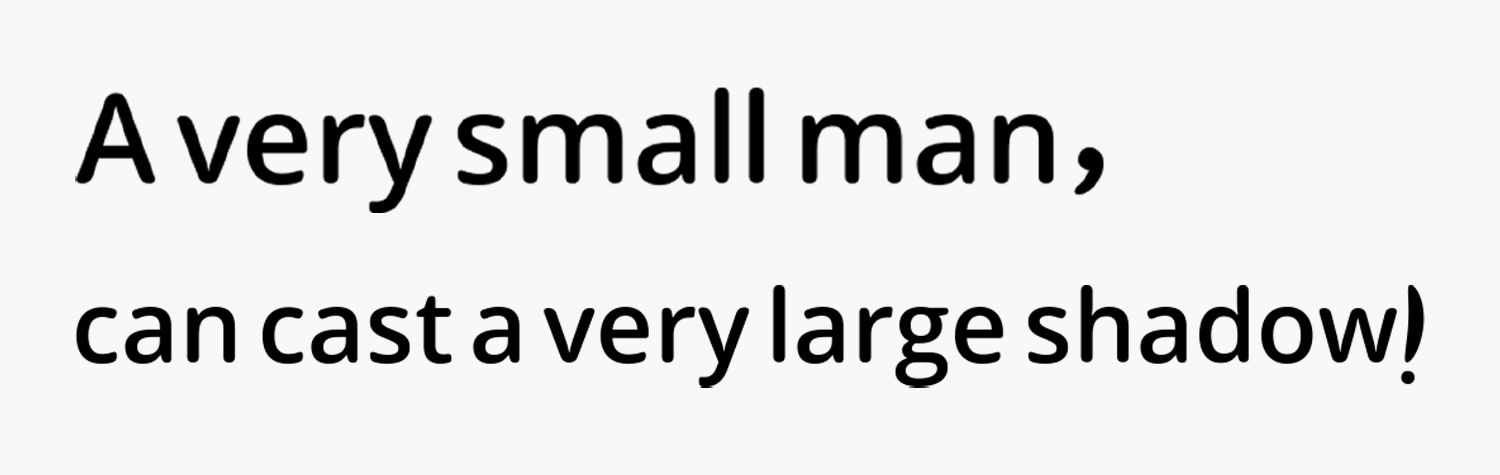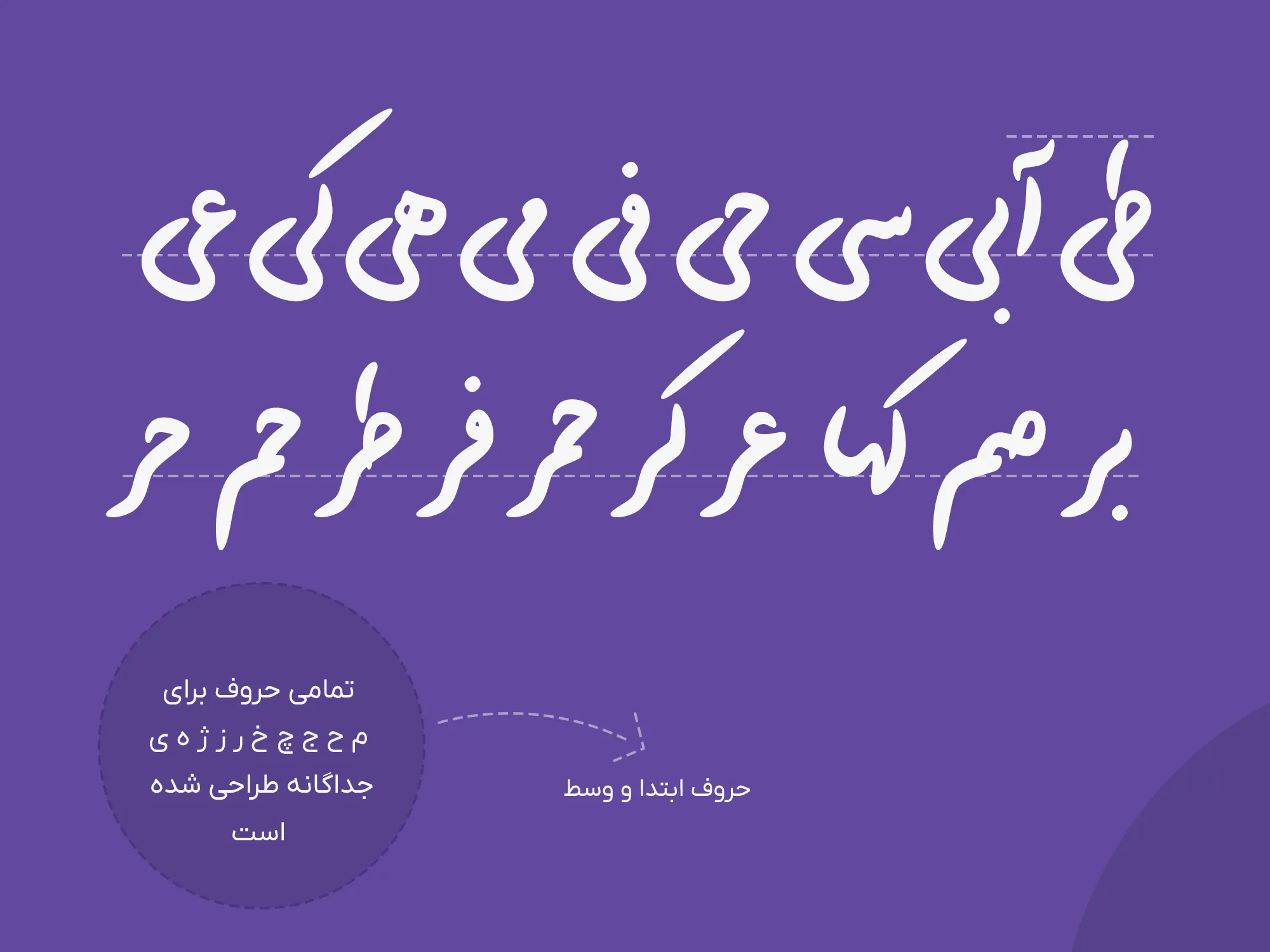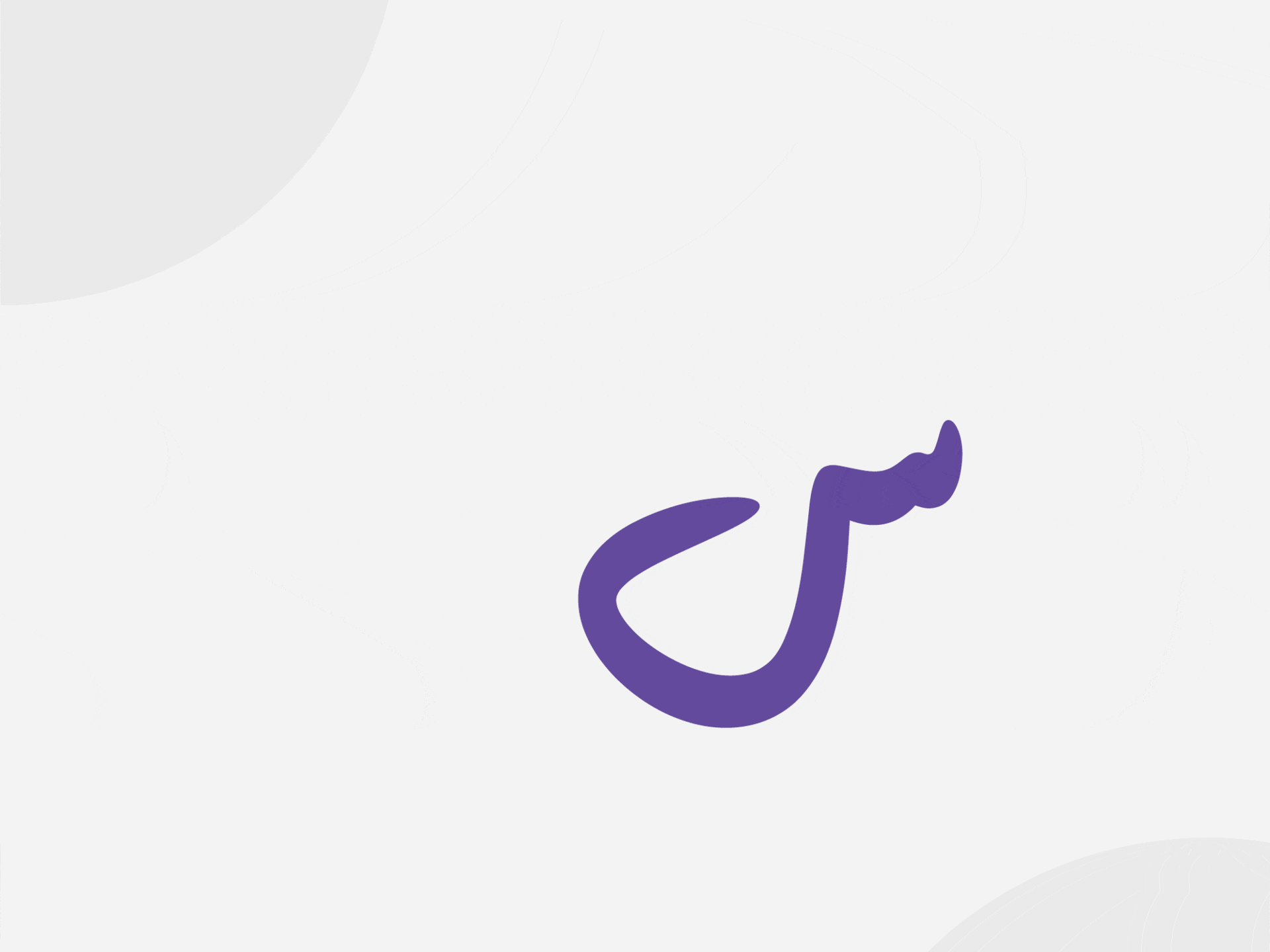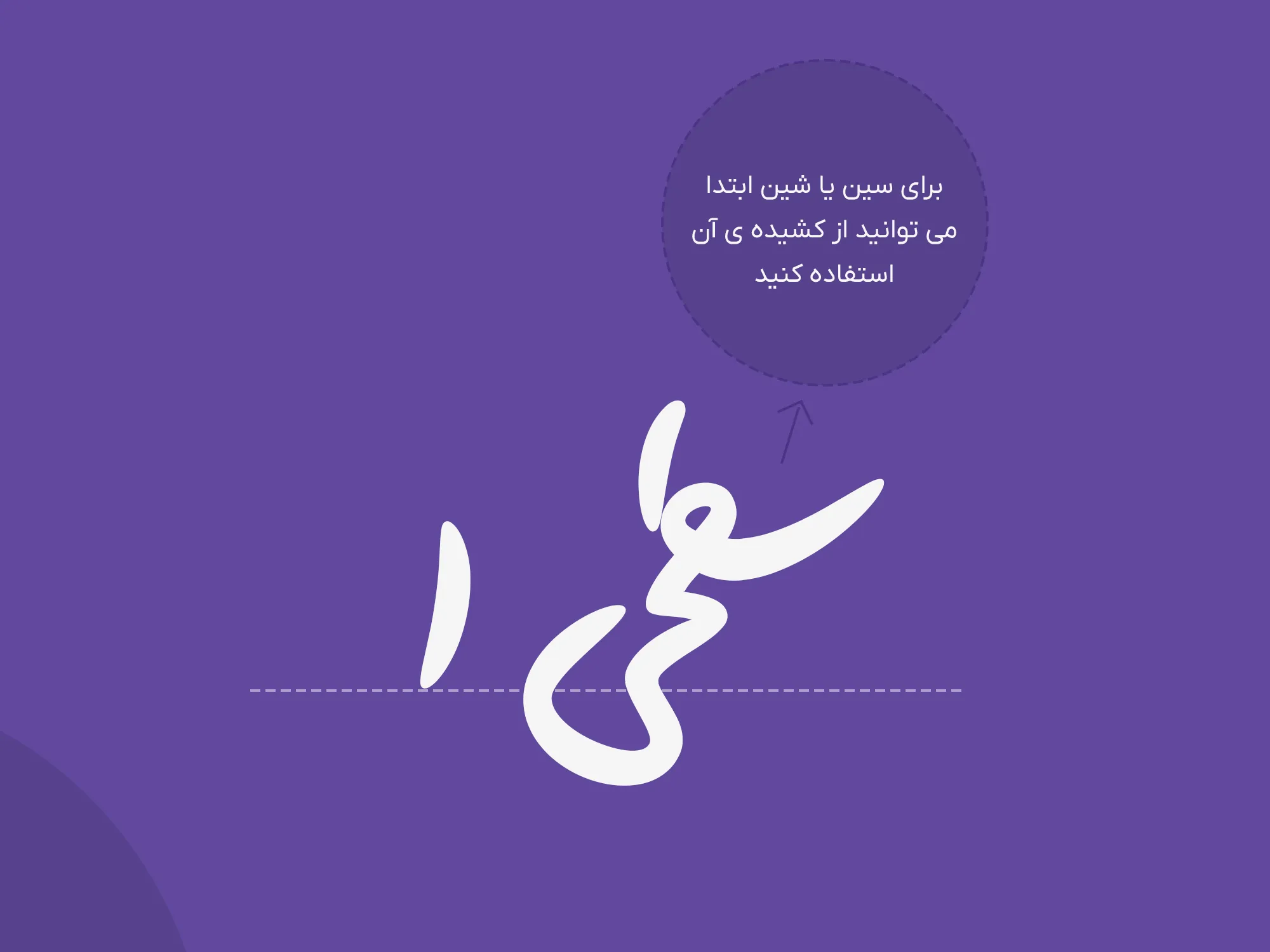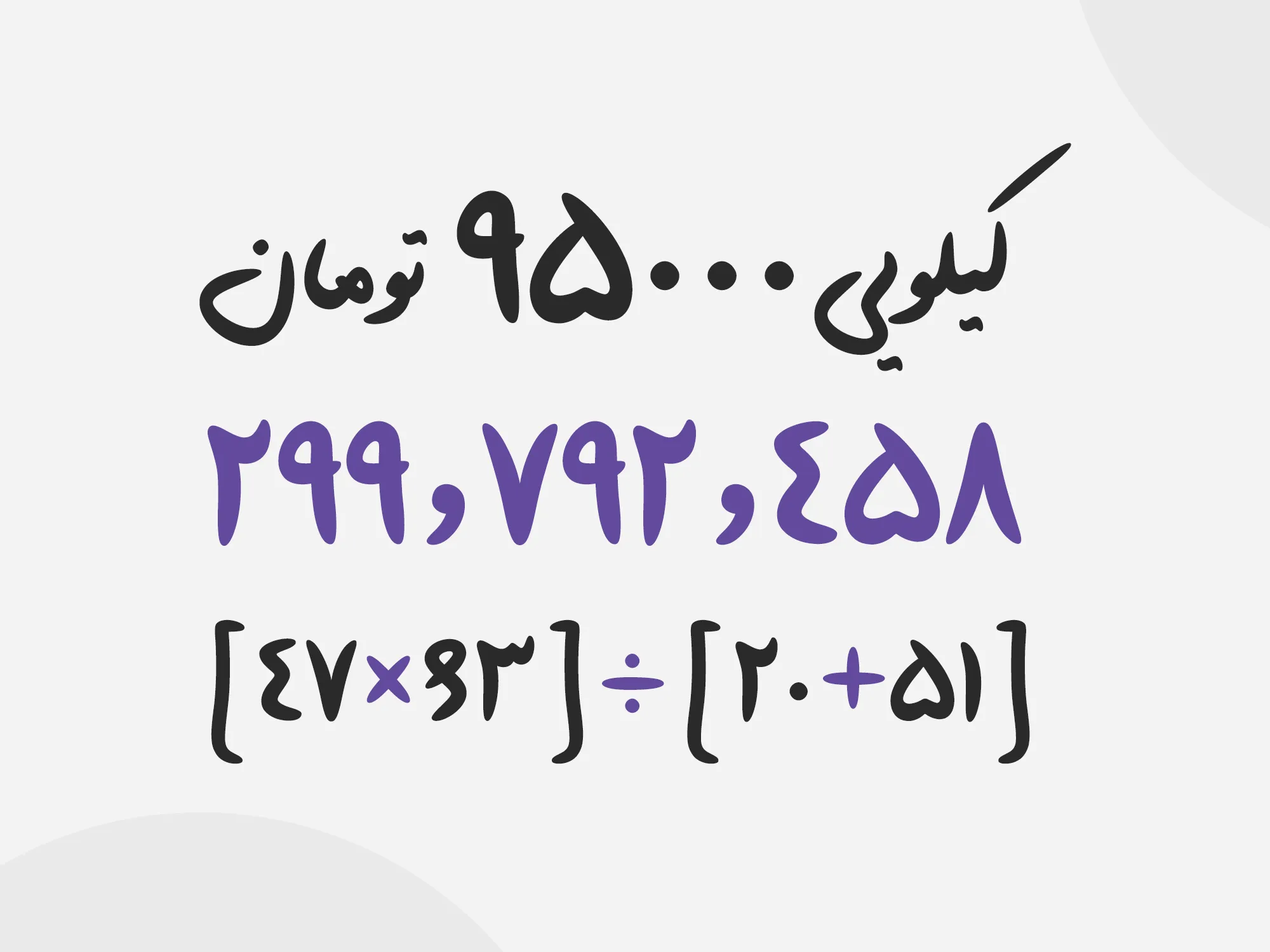
فونت پارسا (Parsa)
فونت پارسا (به انگلیسی: Parsa) جدیدترین فونت فارسی دستنویس است که بر اساس خط نستعلیق و با تکیه بر خط تحریری طراحی شده است که میتوانید از این فونت جدید برای تبلیغات و عناوین استفاده کنید. در ادامه به معرفی و دانلود فونت پارسا خواهیم پرداخت.
قلم پارسا توسط مجید هلاکویی طراحی شده است که چندین سال به عنوان مدرس و طراحی گرافیک تایپ فارسی فعالیت دارد. وی این فونت را در طول ۴ سال مطالعه طراحی کرده است که نتیجه آن را امروزه به این شکل و سیاق میبینیم.
در ادامه این نوشته از سایت فونتچی به معرفی و بررسی فونت جدید Parsa خواهیم پرداخت؛ قلمی که سرشار از ترکیبات جایگزین اختیاری، اجباری و با قابلیت تغییر فاصله کلمات است که میتواند هم برای عناوین و هم تبلیغات روی ایجاد استایلهای سفارشی در قلم بدون نیاز به استفاده از نرمافزارهای گرافیکی هم مناسب باشد.
قلم پارسا نزدیک به خط نستعلیق است که در نگاه اول کاملا میتوان متوجه شد از قلم خاصی برای طراحی حروف از آن بهره برده شده است. این فونت با توجه به پیچیدگیهایی که در زوایا و منحنیها دارد انتخاب خوبی برای تبلیغات خواهد بود.
سبک طراحی و وزن فونت پارسا
با اینکه فونت پارسا نزدیک به خط تحریری و البته کمی هم نستعلیق است، اما شخصیت اصلی متاثر از نوع قلمی است که با آن نوشته شده است. این قلم مانند قلمهای خوشنویسی دارای برشهای تیز نیست و تنوع ضخامت کمی دارد. همچنین به نسبت قلمهای تحریری (خودکاری) بولدتر است.
تفاوت دیگر فونت پارسا با فونتهای تحریری، نزول کمتر در حروف زیر خط کرسی است که باعث پراکندگی کمتری در ترکیبات میشود که آنها را بیشتر در اعراب میبینیم؛ اما با این وجود در قلم پارسا این مشکلات برطرف شدهاند.
فونت پارسا در حال حاضر که نسخه بهبود یافته آن پس از ۴ سال انتشار در دسترس عموم قرار گرفته است از یک وزن معمولی Regular پشتیبانی میکند که حروف دارای ضخامت مناسبی برای استفاده در عناوین هستند.
پشتیبانی از زبان فارسی و عربی
فونت پارسا فارسی است اما با توجه به رسمخط مشترکی که زبان عربی دارد، از این زبان نیز پشتیبانی کاملی دارد. تمامی حروف عربی نظیر «ک، ی، ه، ؤ، ئ» که دارای ساختاری متفاوت از فارسی هستند نیز گلیف استاندارد خود را دارند تا طبق استاندارد از این قلم در این زبان استفاده کنید.
همنشینی حروف نیز در هر دو زبان رعایت شده بهطوری که با قرارگیری اعراب در کنار کاراکترهای «سکون، همزه یا تنوینها» موجب چسبندگی به حروف قبلی یا بعدی نخواهد شد و تمامی حروف و کلمات ساختاری یکپارچه خواهند داشت.
سبک نقطهگذاری در این فونت بهشکل دستنویس بوده و از نقاط گرد برای نقطههای تکی، اما از سبک چسبان برای نقطههای دوتایی و سهتایی به سکل موج استفاده شده است که ظاهر فونت را فانتزی کرده است.
فونت انگلیسی پارسا نیز از یک فونت رایگان اپنسورس الهام گرفته شده است که ظاهری نزدیک به این قلم داشته باشد. با وجود این گلیفها برای زبان انگلیسی دیگر لزومی نخواهد داشت که از فونت دیگری برای زبانهای لاتین استفاده کنید.
هرچند که توصیه میشود اگر بهدنبال سبک نوشتن نزدیکتر به این قلم هستید با استفاده از فونتهای لاتین که ساختاری چند وزن و دارای ظاهری دستنویستر هستند نیز میتوانید استفاده کنید.
دارای ترکیبات جایگزین خودکار برای حروف مختلف
فونتهای دستنویس با ظاهری فانتزی عموما دارای ترکیبات جایگزین فراوانی هستند که میتواند به نمایشیتر کردن فونت و زباسازی برای تبلیغات و عناوین کمک بسیار بزرگی بکند. فونت پارسا فارسی نیز از این قاعده مستثنی نیست و در دل خود حروف اختیاری و اجباری متعددی را دارد که به عنوان سبک جایگزین مورد استفاده قرار میگیرند.
در تصویر بالا نمونهای از ترکیبات و حروف جایگزین فونت پارسا را مشاهده میکنید که بسته به موقعیت قراگیری در کلمات تهیه شدهاند. این ترکیبات برخلاف حروف اصلی بهصورت ترکیبی در نظر گرفته شده که به شکل اجباری وقتی در کنار هم قرار بگیرند سبک نوشتاری تغییر خواهد کرد.
در تصویر زیر نیز نمونهای متحرک از حالت جایگزینی حروف را برای چند کلمه مختلف مشاهده میکنید.
یکی از ویژگیهایی که این فونت در حروف جایگزین دارد، تمرکز روی حروف ابتدایی «سین و شین» است که میتوانید آنها را به صورت کشیده تایپ کرده یا اینکه از نسخه معمولی دندانهدار استفاده کنید.
ویژگی دیگر فونت پارسا در حالت جایگزین قابلیت تغییر حروف «ب، پ، ت، ث، ن، ی» برای زمانی است که در میانه حروف قرار بگیرند. این ساختار نیز بهشکل اجباری موجب تغییر شکل حروف و کلمات خواهد شد.
هدف از همه تغییرات در حروف و کلمات این فونت نمایشیتر کردن فونت است تا در عناوین و تبلیغات بهتر خود را نشان داده و از سوی دیگر مشکلاتی که در تایپ همراه با اعراب بهوجود خواهد آمد مرتفع گردد.
فونت پارسا با اعداد فارسی هک شده
فونت پارسا جز برای اعداد «۴۶» که از نسخه عربی بهره میبرند، در سایر اعداد از نسخه استاندارد فارسی بهره میبرد. همانطور که اشاره شد ساختار این فونت نزدیک به خطوط نستعلیق و تحریری است که دلیل این سبک اعداد نیز همین مسئله بوده است. اما انتظار میرود در نسخههای آتی اعداد فارسی «۴۶» نیز در این فونت گنجانده شود.